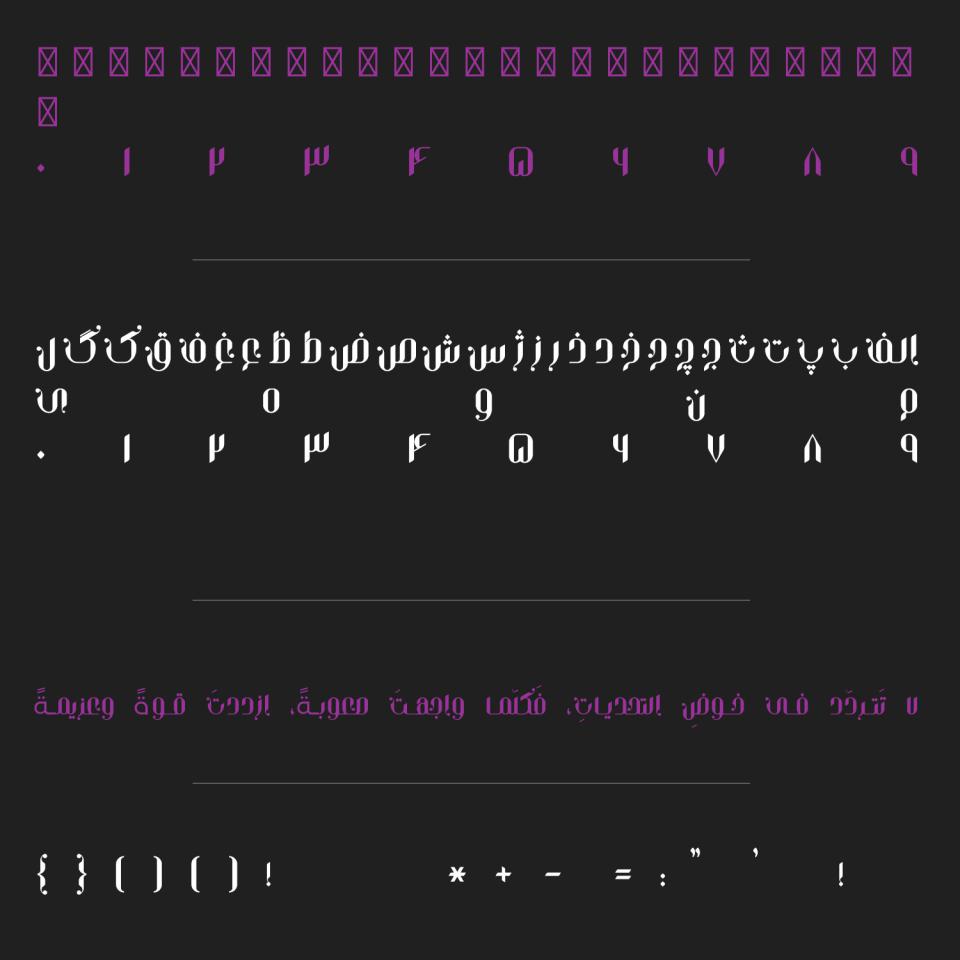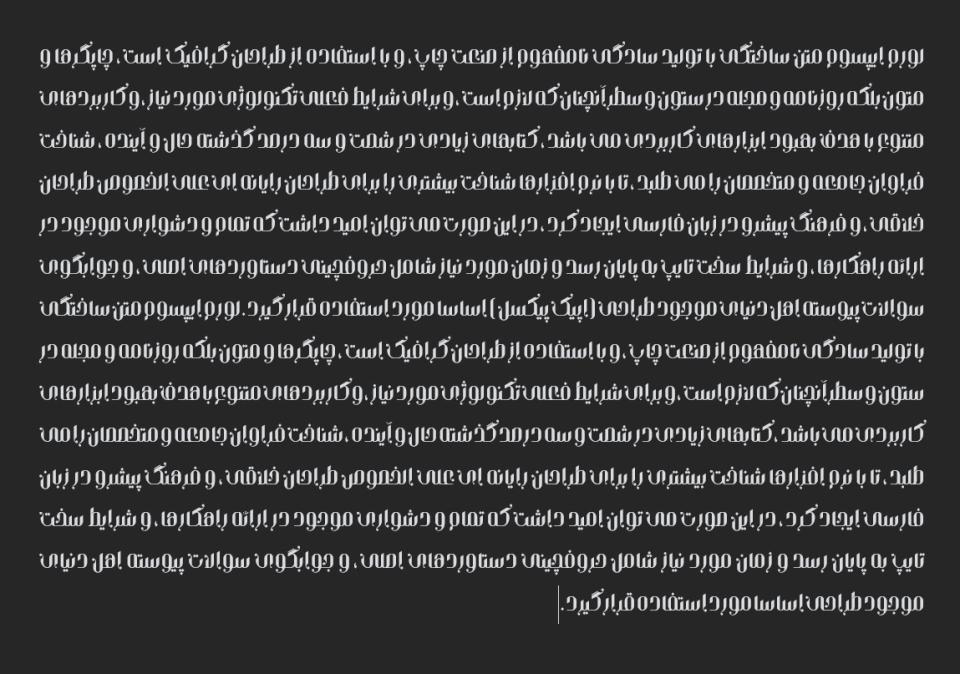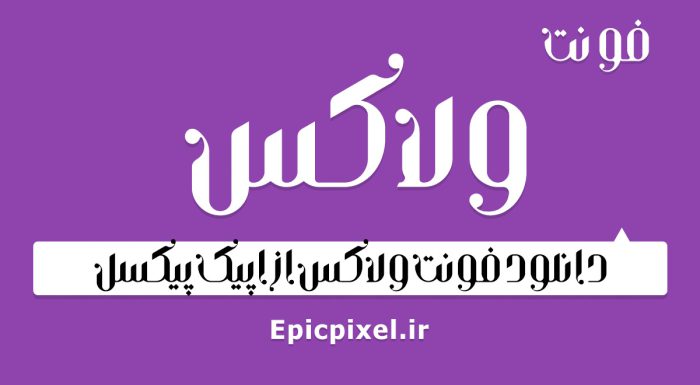
فونت ولاکس فارسی
فونت فارسی ولاکس، با طراحی هندسی و جسورانه اش، برای کسانی که به دنبال جذب نگاه مخاطب هستند، انتخابی ایده آل است. این فونت، با ساختار خاص خود، حسی از خودنمایی و قدرت را به متن می بخشد و برای عناوین و متون کوتاه، جلوه ای ویژه ایجاد می کند. ولاکس، شخصیتی پرشور و پویا دارد و در عین حال که مدرن به نظر می رسد، رگه هایی از اصالت را نیز در خود حفظ کرده است.
یکی از ویژگی های برجسته ولاکس، خوانایی بالای آن در اندازه های مختلف است. این ویژگی، باعث می شود که متن شما، چه در ابعاد بزرگ برای پوسترها و تبلیغات و چه در ابعاد کوچک برای وبسایت ها و اپلیکیشن ها، به راحتی قابل خواندن باشد. با این حال، باید توجه داشت که به دلیل ساختار خاص و نسبتاً فشرده ی حروف، استفاده ی طولانی از آن در متون طولانی ممکن است کمی خسته کننده باشد. بنابراین، بهترین کاربرد آن، در عناوین، تیترها، لوگوها و نوشته های کوتاه و جذاب است.
ولاکس، با وجود ظاهر مدرن، به خوبی با زبان فارسی سازگار است و تمامی حروف و نشانه های فارسی را به درستی پشتیبانی می کند. این فونت، می تواند به طراحی های شما، از جمله طراحی وب، طراحی گرافیک، و حتی تولید محتوای شبکه های اجتماعی، روحی تازه ببخشد. اگر به دنبال فونتی هستید که هم چشم نواز باشد و هم حرفه ای، ولاکس می تواند گزینه ی مناسبی برای شما باشد. این فونت با ویژگی های منحصر به فرد خود، به شما کمک می کند تا پیام خود را به شکلی مؤثر و جذاب به مخاطب منتقل کنید.